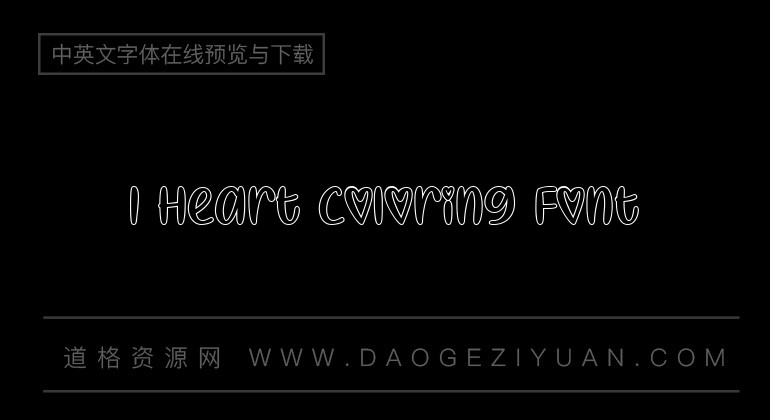
I Heart Coloring Font
I Heart Coloring Font 是一款可爱的手写字体,拥有 26 个大写字母和 10 个数字。这个字体的特殊之处在于,每个字母都有一个填色的版本,可以让你在字体里填充颜色,打印出来后就像是你自己手工着色的一样。 这个字体适合用于制作海报、手信、卡片、标语、教育材料等需要注重个性化和趣味性的设计。如果你喜欢手工制作和DIY,那么这个字体一定能为你的设计加分!
I Heart Coloring Font是一款非常不错的手写艺术字体,具有很好的视觉感,适合于文化类的宣传设计、商业类品牌的广告和产品包装设计以及个性化文字排版等较多场景。